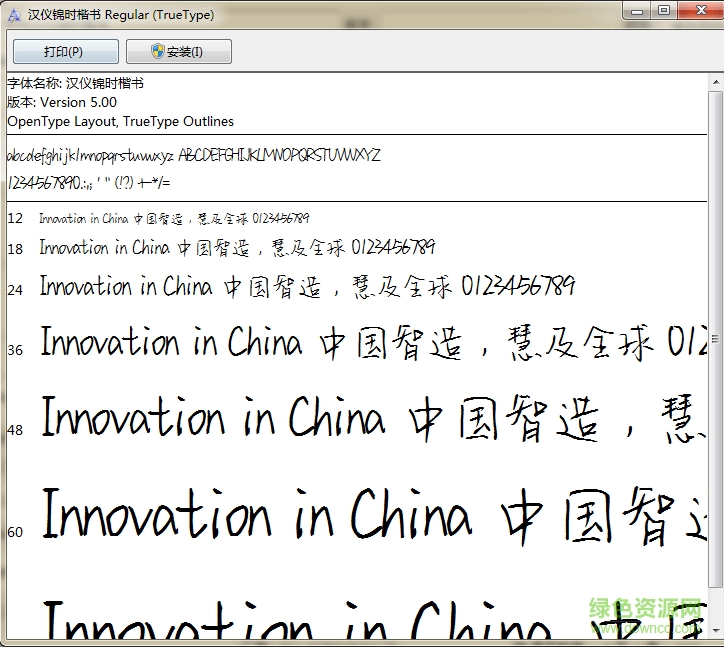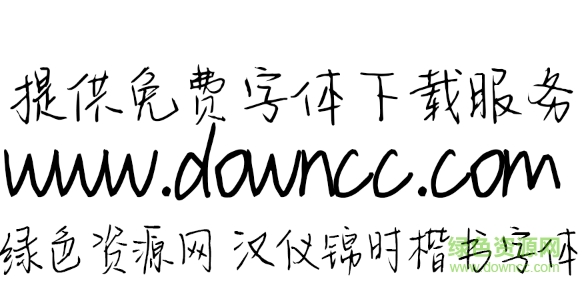
華為漢儀錦時(shí)楷書(shū)
漢儀錦時(shí)楷書(shū)字體這一楷書(shū)字體的運(yùn)用十分廣泛,在時(shí)下這個(gè)數(shù)字化的時(shí)代能夠帶來(lái)更好的字體顯示效果,十分適合打印以及各類(lèi)媒體顯示行業(yè), 能夠更好的帶給你用戶(hù)視覺(jué)上的沖擊效果!
漢儀錦時(shí)楷書(shū)ttf介紹
為你實(shí)現(xiàn)一種全新的含義字體的使用效果,擁有最全面的視覺(jué)體驗(yàn),帶給你各種行云流水般的使用效果,在文字創(chuàng)作以及字幕制作中都能夠使用這款十分精美的字體!
漢儀錦時(shí)楷書(shū)ttf
特色介紹
1、擁有獨(dú)特的線(xiàn)條效果
2、棱角分明給你不錯(cuò)的視覺(jué)欣賞
3、更加清晰的表現(xiàn)出文字的各類(lèi)行文結(jié)構(gòu)